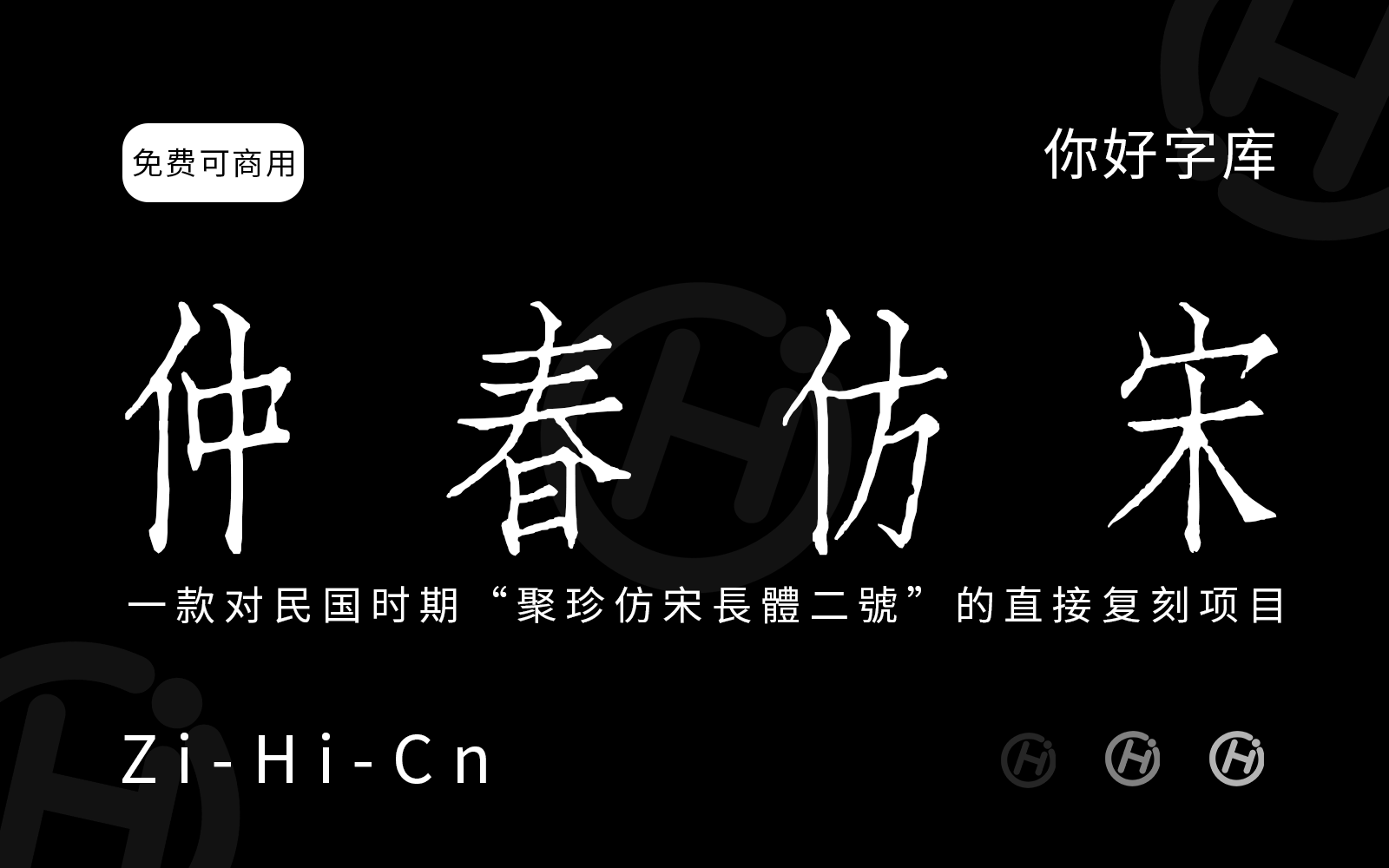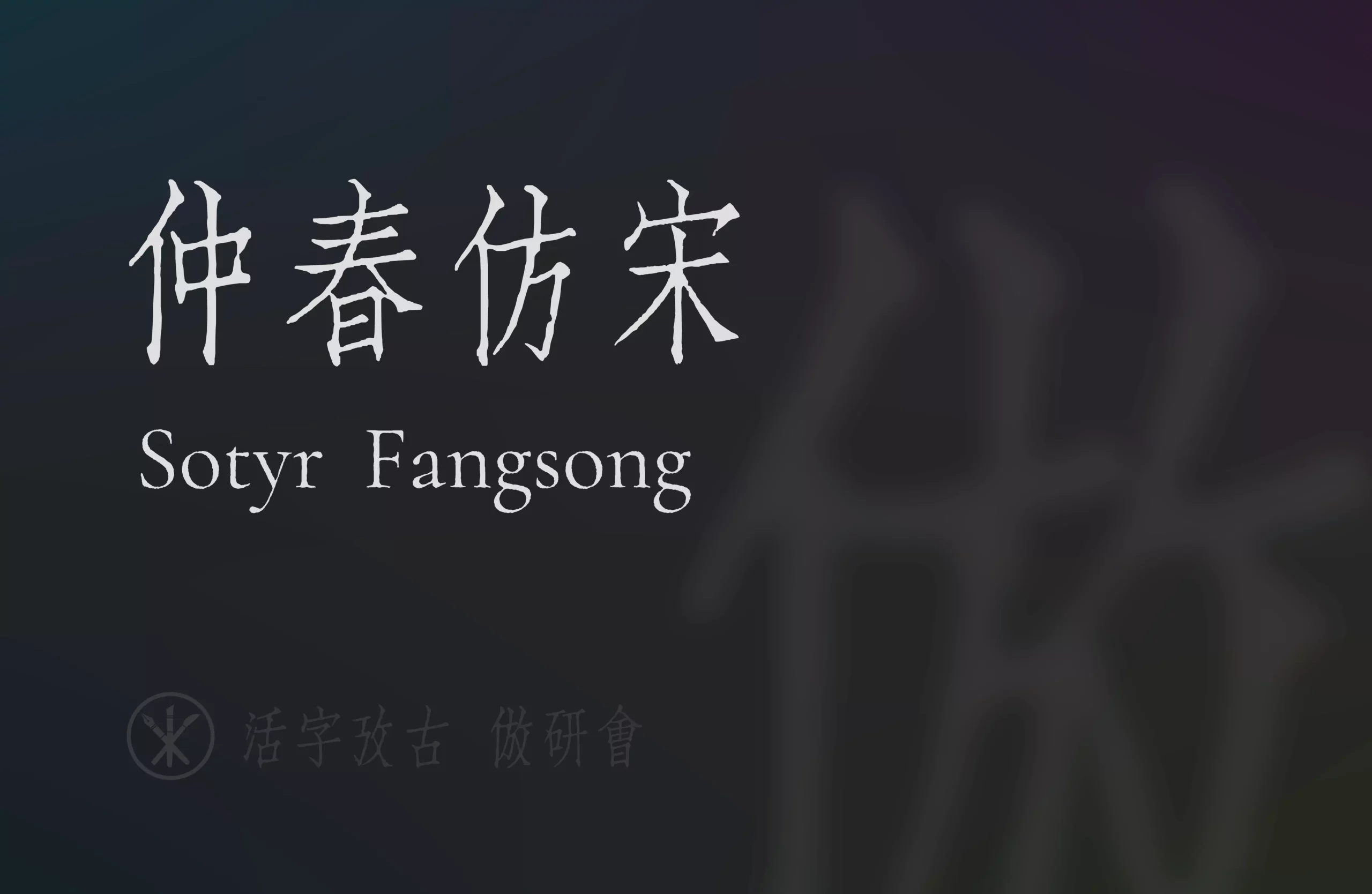
仲春仿宋
“仲春仿宋”是一款由聚珍數位文創(JuZhen Digital Creation)开发的免费开源中文字体,测试版 v0.1 于2025年5月3日发布。它属于衬线风格,是对民国时期“聚珍仿宋長體二號”的直接复刻项目,旨在还原早期印刷宋体体的古典韵味。这款字体基于“思源宋体”调整,字形优雅,笔画横细竖粗,带有传统仿宋的装饰性衬线,展现出硬朗的印刷美感。
仲春仿宋包含约7000个字符,覆盖GB2312标准的6763个汉字,支持简体中文、部分繁体中文及基本符号。它以SIL Open Font License 1.1授权,个人和商业用途均免费。